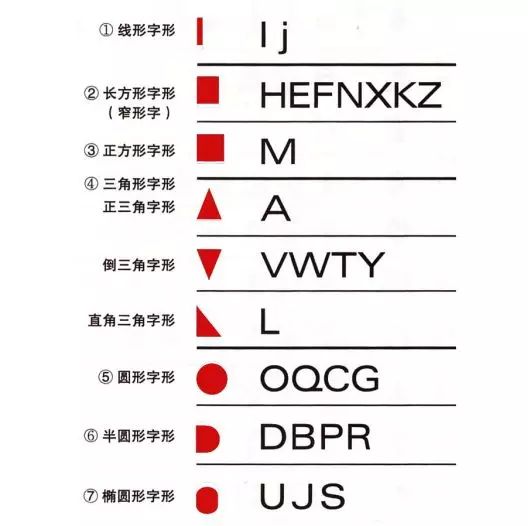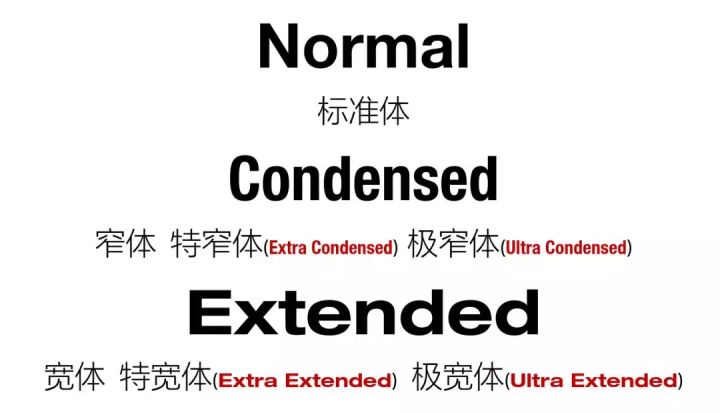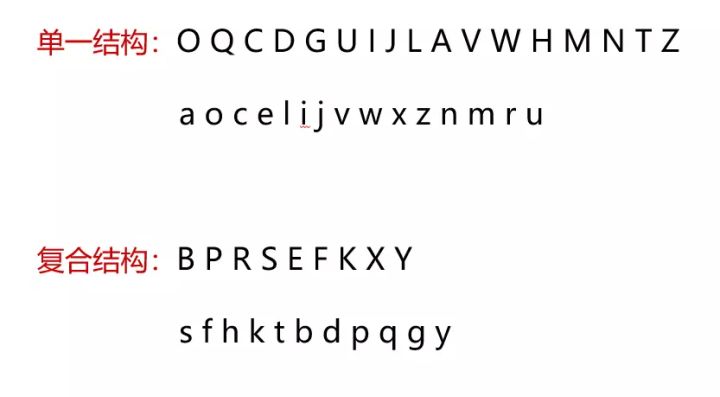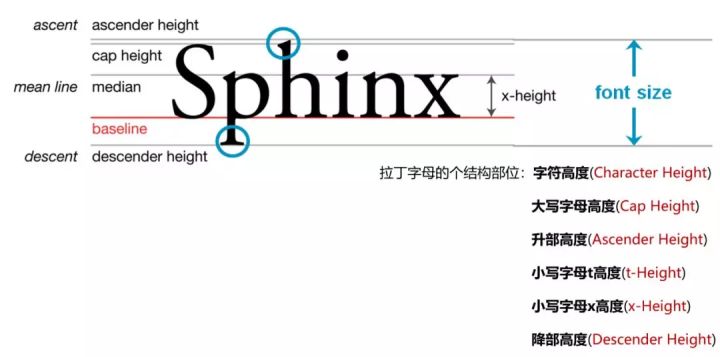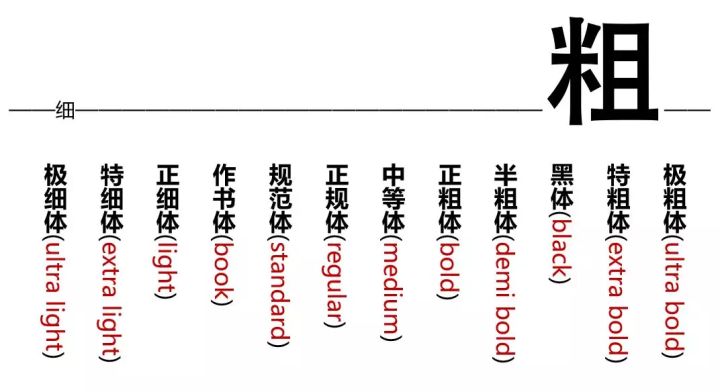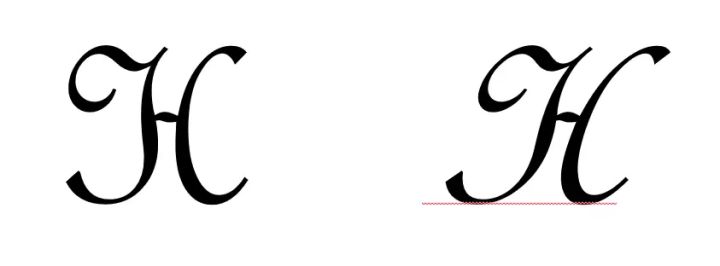
对于字形,你了解多少?找准设计入手的方向,为作品集的创作带来更多启发。
平面设计以“视觉”作为主要的沟通和表现方式,这其中,自然包含字体设计,对于很多初学字体设计的人来说,临摹仅是第一步。字体设计尽精微、而致广大,需要打好坚实的基础,才能厚积薄发,将字体设计出彩。以现代拉丁字母为例,其基础概念包括字形、字体、字库、字系、字符等多方面。
本文阐述了现代拉丁字母中字形(Glyph)的概念,明晰字体不同类别的基础要点,找准设计入手的方向,为作品集的创作带来更多启发。
一、字形(Glyph)的概念
字形,从非语言学角度来看,特指单个字符(字母、符号、标点、记号等等)的笔画组成的文字形状、字体幅度、结构比例、衬线体的衬线造型、粗细黑度等等。字形是一个图像符号抽象出来的二维造型,其个体本身就可以看成一个图形表现。
二、字形的设计方向
1. 文字形状
在设计字形时,首先需要考虑的是文字形状。拉丁字体在漫长的发展中逐渐形成了便于书写、识别且简洁的多种文字形状供大家选择,如方形、长方形、三角形、圆形等等,任何字体设计都是基于基础形状的研发。如果没有文字形状作为基准,那同一字体将成为一盘散沙。
2. 字幅
由于拉丁字体包含矩形、圆形、三角形三种基本形状,其组合变化又较为复杂(如大小写)。因此,西文自古横向排列,字高相对统一,字面宽度因字而异。这种尺度差异叫做“字幅差”。
3. 结构与比例
1)结构与比例
拉丁字母是由圆弧和直线组成的几何形结构,可归纳为方、圆、三角3种基本形状,即H、O、A,并可分为单一结构和复合结构,即O、B,在宽窄上又有4*4、4*3、4*2之分,即M、A、S。
拉丁字母本身就已经具备了美的元素,是人们长期从事书写艺术的结晶,但拉丁字母的结构和比例并非绝对的,同学们在设计时,应根据自己的主题及内容等情况进行调整加工。
拉丁字母的高度设计包括字符高度、大写字母高度、升部高度、小写字母x高度、小写字母t高度、降部高度这几个结构部位,它们之间的比例关系即构成了大多字体的结构比例。且易读、易识别,同时具备拉丁字体的独特美感。如下图所示,除去小写字母t高度之外,拉丁字体被如同拼音四线格一样的“四线谱”所控制。
2)内收与扩展
拉丁字母中,字母的结构是内收还是扩展,是由小写字母x的高度(x-height)决定的。x高度小,字体的整体结构就向内收,由于视觉,小写字母的字身就会缩小。反之,字身就会变大。因此x高度被称为拉丁字体的相对度量单位,在设计中起着至关重要的作用,也是同学们在设计时需要最先考虑的字母。
在不同时代、不同要求、不同背景下,有着不同的高低变化。如果是强调可读性文字设计的情况下,大部分字体的上伸部分和下伸部分会预留出很大空间。
通常,字体中小写x字母的高度,既然是一个相对度量单位,那因字型的不同就会产生多种不同的变化。X高度就相当于时尚界中裙子的长度,会因为时尚的改变而有长短变化,为了保障字体的可读性,大部分字体都需要给升部高度和降部高度预留出很大空间。从下图中可以看出,虽然每个字体具有相同的磅值,然而他们x高度明显不同。
4. 线幅(Weight,或黑度)
线幅是指字或字母比划的粗细级别,也可以成为字体分量。不过,要比较不同字体的粗细,需要在字符高度相同的前提下进行比较才可获得准确认知。
5. 笔画造型与线端造型(衬线体与无衬线体)
1)笔画造型
笔画造型是构成文字视觉风格的关键,也是创造文字审美,形成不同字体造型、风格的重要条件。因而不同的字体有着不同的笔画造型及风格。
2)线端造型
是指文字笔画末端的形态,是形成文字视觉风格的点睛之处。尤其针对衬线字体情况下,虽小,确实关键所在。笔画造型和线端造型共同打造出文字的视觉形态与风格特点。
6. 斜体(Italic)
斜体是为衬线体专门绘制的一种特有字体,比直立的正体字(Roman)要窄,部分细节的曲线是从手写体衍生而来的,因此在字体造型上保留有许多书法风格,而且有连写,可以紧凑排列。不同字系的斜体,其字干倾斜的角度各有不同。
7. 伪斜体(Oblique)
伪斜体是在正体字(Roman)样式基础上,通过单纯倾斜实现的一种字体样式。虽然样式上与斜体很相近,但风格上已没有书法细节。无衬线体通常大部分都有伪斜体,但有一小部分是例外,例如吉尔gill sans和古蒂goudy sans。
Final: 其实,基本上每一款正体都有与之相对的、以中轴线为基准、向右做出倾角在7度到20度之间的不同角度的倾斜字体。虽然只是简单的倾斜,但却包含斜体与伪斜体两种完全不同概念的字形,在设计时也要分清两者的概念。
字体设计需要具有准确传达信息的辨识性、视觉上的美观性,以及自己个性化的表达,在创作相关项目时,合理使用字体、字形、字库、字系、字符等概念进行设计及加工,能够体现出自己对于专业能力的合理运用及把控,同时向考官进一步展现了自己在设计中全面的思考及探索。